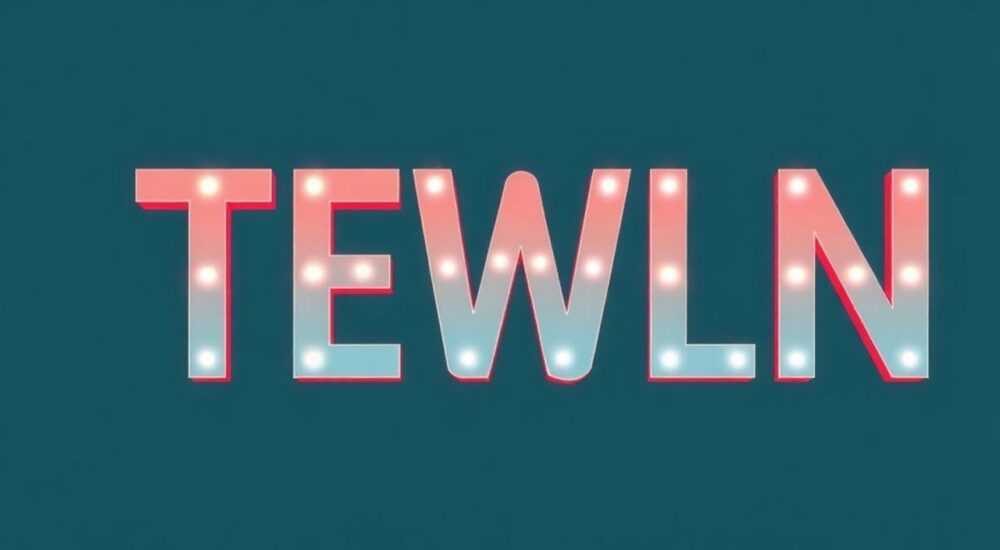
Как сделать красивый шрифт фотошоп
Создание красивого шрифта в Photoshop — это сочетание технических навыков, понимания типографики и художественного чутья. Многие дизайнеры начинают с выбора подходящего шрифта из библиотеки, но истинная красота достигается за счёт настройки контуров, добавления эффектов, работы со светом и тенью, а также гармоничного вписывания текста в общую композицию. Красивый шрифт не просто привлекает взгляд — он усиливает сообщение, вызывает нужные эмоции и запоминается.
Выбор подходящего шрифта для основы
Первый шаг к созданию красивого шрифта — правильный выбор исходного типа. Даже самый продвинутый дизайн не спасёт плохо подобранный шрифт. Важно учитывать контекст: логотип, рекламный баннер, обложка книги или социальные сети — каждая задача требует своего подхода. Например, для детской тематики подойдут округлые, игривые шрифты, а для делового письма — строгие серифные.
Существует несколько ключевых категорий шрифтов:
- Серифные — имеют засечки, ассоциируются с классикой, надёжностью (Times New Roman, Georgia).
- Беззасечные — современные, чистые формы (Helvetica, Arial, Roboto), идеальны для цифровых экранов.
- Рукописные — имитируют почерк, передают индивидуальность (Brush Script, Pacifico).
- Декоративные — используются для акцента, но не рекомендуются для больших объёмов текста.
Тип шрифта |
Где использовать |
Примеры |
Серифные |
Книги, журналы, официальные документы |
Georgia, Garamond, Baskerville |
Беззасечные |
Сайты, мобильные приложения, презентации |
Roboto, Open Sans, Montserrat |
Рукописные |
Приглашения, логотипы, бренды с «человеческим» лицом |
Lobster, Caveat, Dancing Script |
Декоративные |
Заголовки, плакаты, реклама |
Bebas Neue, Impact, Blackletter |
Преобразование текста в вектор и работа с контурами
После ввода текста в Photoshop важно сразу решить: будете ли вы редактировать его как текст или превратите в векторные контуры. Преобразование в вектор позволяет изменять форму букв на уровне путей, что открывает огромные возможности для кастомизации.
Чтобы преобразовать текст в контуры:
- Выделите текстовый слой в панели слоёв.
- Щёлкните правой кнопкой мыши и выберите «Создать контуры» (или «Преобразовать в кривые»).
- Теперь текст становится векторным объектом, который можно редактировать инструментом «Перо» или «Прямой выбор».
После преобразования вы теряете возможность редактировать текст обычными средствами (например, менять буквы через клавиатуру). Поэтому опытные дизайнеры часто дублируют текстовый слой перед конвертацией — один оставляют как резервный, второй превращают в контуры.
Работа с контурами даёт контроль над каждой точкой буквы. Вы можете удлинять штрихи, менять угол наклона, расширять или сужать элементы. Например, чтобы придать шрифту более «роскошный» вид, можно удлинить верхние засечки или добавить завитушки в нижней части букв.
Настройка интерлиньяжа, кернинга и трекинга
Даже самый красивый шрифт может выглядеть дешево, если игнорировать пробелы между символами. Типографика — это не только форма букв, но и пространство вокруг них. В Photoshop есть три ключевых параметра:
- Кернинг — регулирует расстояние между двумя конкретными буквами (например, «А» и «V» часто сближают).
- Трекинг — равномерно изменяет интервал между всеми символами в выделенном фрагменте.
- Интерлиньяж — расстояние между строками текста.
Правильная настройка этих параметров делает текст визуально сбалансированным. Например, слишком плотный кернинг может создать ощущение давления, а чрезмерный — размытость. Оптимальное значение зависит от размера шрифта и контекста.
Для заголовков часто используется отрицательный кернинг, чтобы буквы плотнее прилегали друг к другу. В то же время длинные абзацы требуют увеличенного интерлиньяжа — обычно на 120–145% от размера шрифта.
Эффекты слоя: как придать шрифту глубину и стиль
Один из главных инструментов красоты шрифта в Photoshop — стили слоя. Они позволяют добавить объём, свет, тень и текстуру без необходимости рисовать всё вручную. Доступ к ним — двойной щелчок по слою или кнопка «fx» внизу панели слоёв.
Основные стили, которые стоит освоить:
- Тень — внешняя и внутренняя. Создаёт ощущение парения или вдавленности.
- Обводка — позволяет добавить контур вокруг букв. Полезно для контрастного выделения.
- Наложение градиента — делает шрифт многоцветным, добавляет современное звучание.
- Текстура — имитирует бумагу, металл, дерево и другие поверхности.
- Тиснение — создаёт эффект рельефа, особенно хорошо смотрится с крупными шрифтами.
Комбинируя эффекты, можно добиться сложных визуальных решений. Например, градиент + тень + лёгкая текстура дерева — идеально для логотипа крафтового бренда.
Ручная корректировка и создание уникальных форм
Когда стандартные шрифты и эффекты не дают нужного результата, наступает время ручной работы. Создание собственного шрифта — это высший пилотаж типографики. Но даже частичная модификация существующего шрифта может выделить ваш дизайн.
Шаги для ручной корректировки:
- Преобразуйте текст в контуры.
- Используйте инструмент «Прямой выбор» (A), чтобы выделить отдельные точки.
- Перемещайте, добавляйте или удаляйте узлы с помощью инструмента «Перо».
- Добавьте новые элементы — завитки, капли, геометрические формы.
Например, можно превратить обычный sans-serif шрифт в каллиграфический, удлинив вертикальные штрихи и добавив наклон. Или превратить буквы в минималистичные иконки, убрав лишние детали.
Для вдохновения изучайте работы известных типографов: Эрика Спикермана, Маттиаса Клейнера, Александра Коржакова. Их подходы к форме, весу и ритму букв помогут вам развить глаз.
Цвет, градиенты и текстуры для шрифта
Цвет — мощный инструмент воздействия на восприятие. Красный вызывает тревогу и энергию, синий — доверие, зелёный — природу и рост. При выборе цвета шрифта учитывайте не только психологию, но и контраст с фоном.
Градиенты особенно популярны в современном дизайне:
- Линейный градиент — от одного края к другому.
- Радиальный — от центра к краям.
- Угловой — по кругу, создаёт эффект радуги.
Чтобы применить градиент к шрифту:
- Выделите текстовый слой.
- Откройте «Стили слоя» → «Наложение градиента».
- Выберите нужный тип и подберите цвета.
- При необходимости добавьте шум или дithering для более естественного вида.
Текстуры добавляют тактильность. Можно использовать сканированную бумагу, фактуру бетона или ткани. Просто поместите текстуру выше текстового слоя и установите режим наложения «Перекрытие» или «Мягкий свет».
Как вписать шрифт в композицию дизайна
Красивый шрифт сам по себе — не цель. Он должен работать в рамках всей композиции. Учитывайте принципы визуальной иерархии: размер, цвет, положение и контраст определяют, на что зритель смотрит первым.
Рекомендации:
- Главный заголовок — крупный, жирный, занимает 30–40% площади.
- Подзаголовок — меньше, но с достаточным контрастом.
- Основной текст — читабельный, с хорошим интерлиньяжем.
Также важно соблюдать правило трёх шрифтов: не используйте больше трёх разных начертаний в одном проекте. Это предотвращает визуальный хаос.
«Сегодня многие дизайнеры полагаются только на эффекты Photoshop, забывая о фундаменте — типографике. Красота шрифта начинается с пропорций, ритма и баланса. Да, градиент и тень могут впечатлить, но если буквы плохо читаются или несоразмерны — проект провален. Я всегда советую студентам: сначала изучите историю шрифтов, потом уже экспериментируйте с фильтрами.»
— Артём Лебедев, дизайнер, основатель студии Артёмия Лебедева
Создание красивого шрифта в Photoshop — это не просто набор эффектов, а целостный процесс, сочетающий выбор основы, точную настройку пробелов, ручную корректировку и гармоничное вписывание в дизайн. Ключ к успеху — баланс между техникой и художественным чутьём.
- Выбирайте шрифт с учётом контекста и аудитории.
- Преобразуйте текст в контуры для свободной редакции.
- Настройте кернинг, трекинг и интерлиньяж — это критично для восприятия.
- Используйте стили слоя умеренно, делая акцент на качестве, а не количестве эффектов.
- Вписывайте шрифт в композицию, соблюдая иерархию и визуальный баланс.